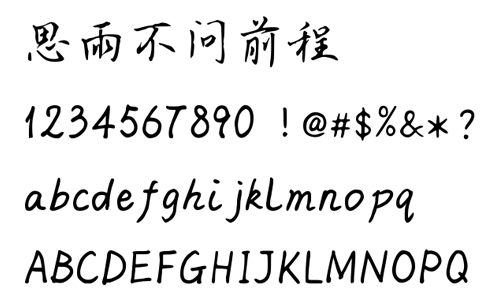
思雨不問前程是思雨字庫推出的一款硬筆手寫書法字體,酸甜苦辣世間味,相攜回味情亦然。舉案齊眉至白首,不枉芳華付此生。該字體是在國家標準簡體字庫GB2312所包含6763漢字的基礎上,又增加了近200常用字,已經(jīng)覆蓋了大陸99.75%的漢字使用頻率,足以滿足日常需求。歡迎喜歡思雨不問前程字體的朋友前來下載使用。